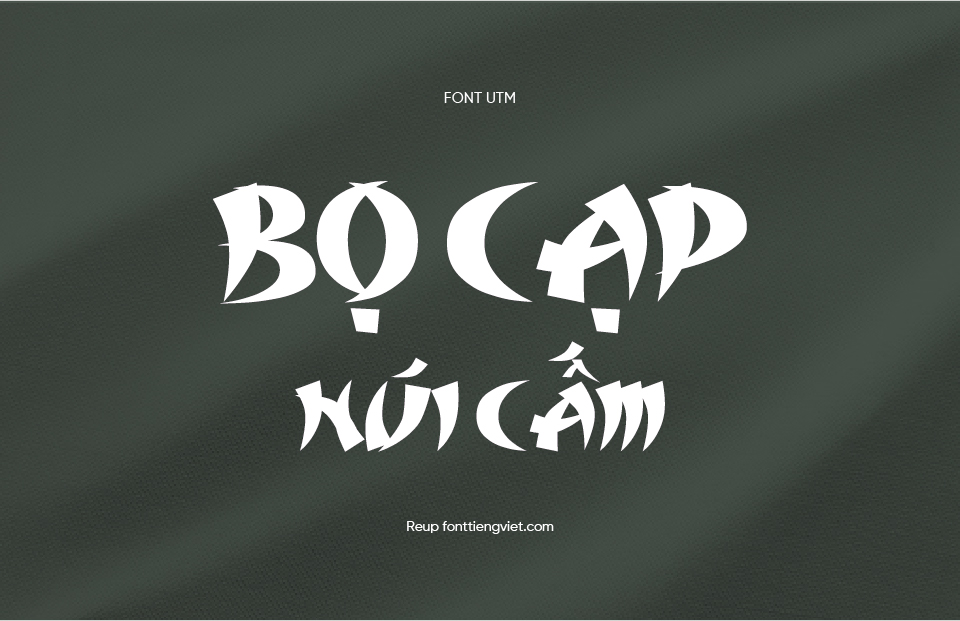
Font Việt hóa UTM Karate
Giới thiệu về bộ Font Việt hóa UTM Karate
Trong thế giới đồ họa hiện đại, việc tìm kiếm một bộ Font Miễn Phí chất lượng là điều vô cùng cần thiết đối với học sinh và sinh viên. Font Việt hóa UTM Karate nổi lên như một lựa chọn hàng đầu nhờ phong cách mạnh mẽ, dứt khoát và mang đậm hơi thở võ thuật truyền thống. Đây là bộ font được chuyển ngữ chỉn chu, giúp người dùng dễ dàng gõ tiếng Việt có dấu mà không lo lỗi hiển thị. Với các đường nét mô phỏng nét bút lông linh hoạt, bộ chữ này mang lại cảm giác năng động, rất phù hợp cho các bài thuyết trình, poster sự kiện trường học hoặc các ấn phẩm truyền thông trẻ trung.
Đặc điểm nổi bật của Font Việt hóa UTM Karate
Phong cách thiết kế độc đáo
Đúng như tên gọi, Font Việt hóa UTM Karate mang trong mình tinh thần của những đường quyền dứt khoát. Cấu trúc chữ cái được thiết kế với độ dày vừa phải, các nét hất và nét sổ tạo nên sự cân bằng hoàn hảo giữa nghệ thuật thư pháp và xu hướng hiện đại. Điều này giúp tác phẩm của bạn luôn có sức hút thị giác cực mạnh.
Khả năng ứng dụng đa dạng
Không chỉ giới hạn trong các chủ đề thể thao, bộ font này còn cực kỳ hiệu quả khi dùng làm tiêu đề cho sách, bìa tạp chí hoặc logo thương hiệu. Nhờ bảng mã Unicode chuẩn, bạn có thể sử dụng mượt mà trên nhiều phần mềm thiết kế chuyên dụng như Photoshop, Illustrator hay thậm chí là các ứng dụng văn phòng cơ bản như Word và PowerPoint.